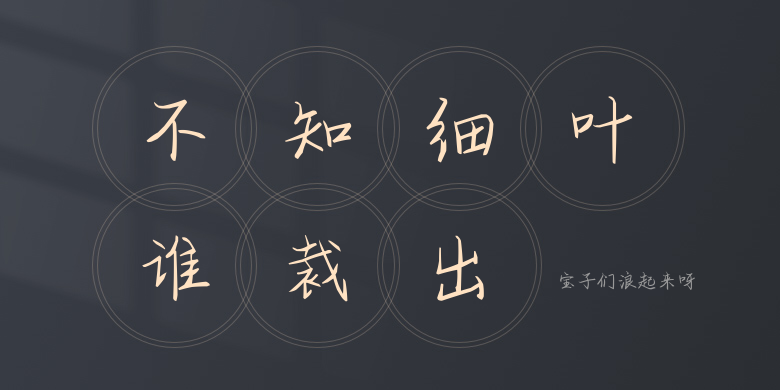
宝子们浪起来呀
宝子们浪起来呀,这款字体结构工整、笔画清晰,兼顾美观与易读性,适用于标题、正文、海报、包装、LOGO 等多种场景。字形优雅稳定,风格百搭耐看,适配日常排版与创意设计,让文字呈现更舒适、更具质感。宝子们浪起来呀一笔一画,皆是细节,以均衡的比例、流畅的线条打造舒适视觉体验,字形端正大气,风格简约现代。无论是商业设计、品牌宣传还是日常排版,都能轻松驾驭,让文字更有格调与力量。宝子们浪起来呀字体下载。